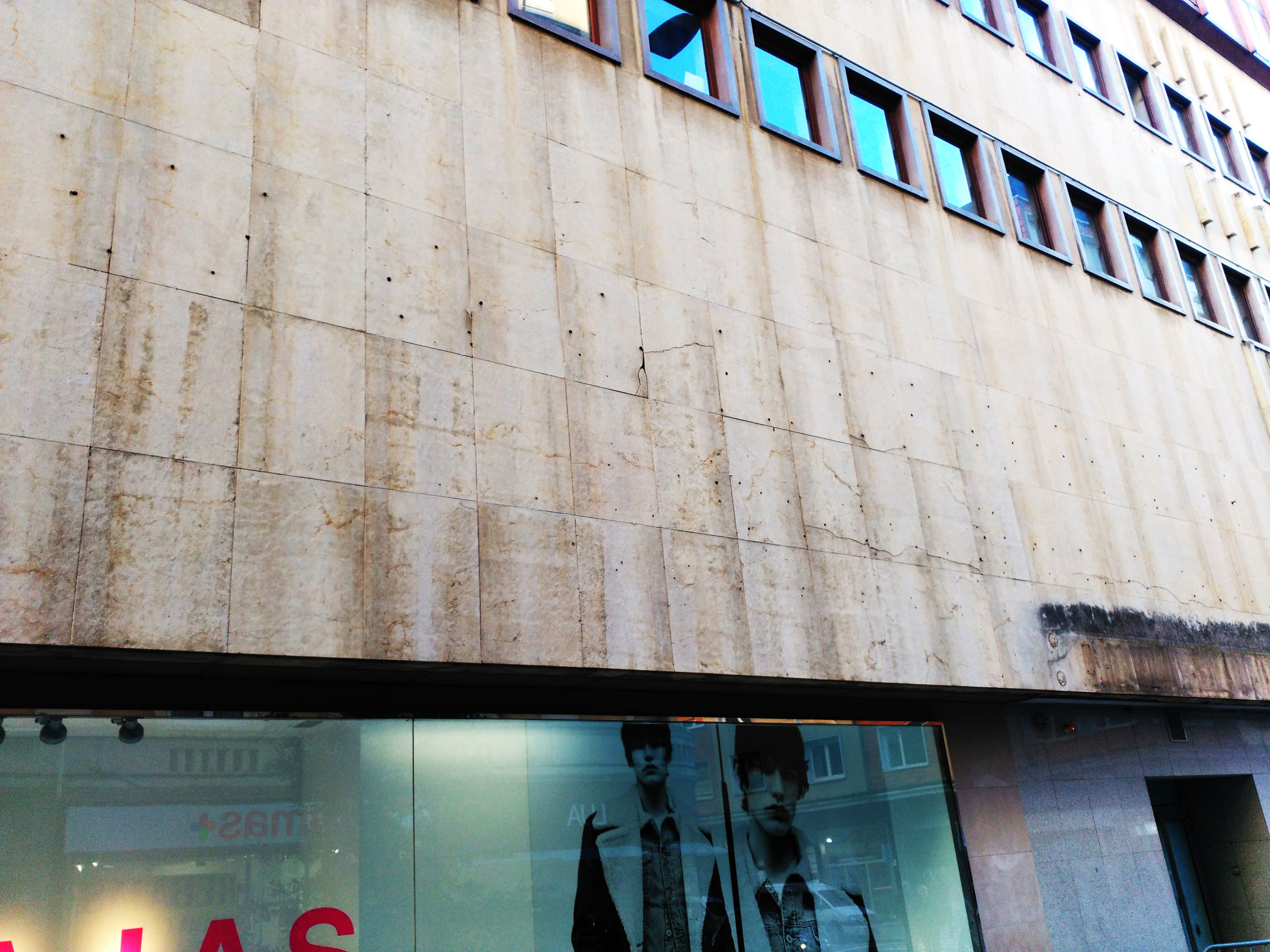
Leyendo en las paredes: Woolworth
Gracias a esta magnifica entrada que ha hecho el blog «Escenas de Santander» sobre la calle Lealtad, y recordando entre otros a los míticos Grandes Almacenes Woolworth, donde hoy está una conocida cadena de ropa, pues deciros que si os paráis y os fijáis en la fachada, aún podéis leer su rótulo.
A través de los puntos de anclaje de las piezas, podemos deducir la forma de las letras, y por tanto «leer». En Santander hay algún otro ejemplo, o en Torrelavega, donde se ve claramente que ponía aquellos viejos rótulos.
Esta técnica es utilizada en la epigrafía, para poder leer aquellas inscripciones en las que las letras de bronce ya han desaparecido, pero ha quedado su agujeros. Así que si os queréis entretener un poco buscar esas letras que ya no están y veréis como aparecen.